خط متغير
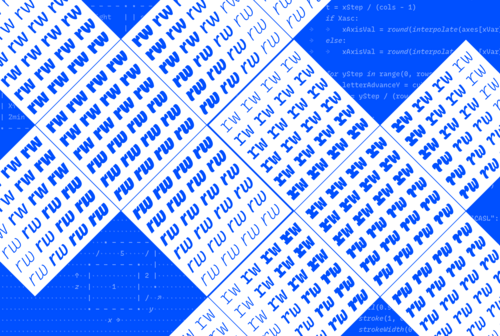
الخط المتغير (VF) هو ملف خط قادر على تخزين نطاق متصل من متغيرات التصميم. يمكن تخزين نمط خط كامل (عائلة خط) في مثل هذا الملف، مع توفر عدد لا نهائي من الخطوط للاختيار من بينها. [ 2 ]
نشأت تقنية الخطوط المتغيرة في تنويعات خطوط TrueType GX من Apple . وتم تكييف هذه التقنية مع OpenType كخطوط OpenType المتغيرة (OTVF) في الإصدار 1.8 من مواصفات OpenType. [ 3 ] [ 4 ] [ 5 ] أعلنت كل من Adobe و Apple و Google و Microsoft عن هذه التقنية في سبتمبر 2016. وقد مهد توحيد هذه الميزة في OpenType الطريق لدعمها في العديد من منصات البرامج. [ 3 ] [ 6 ] [ 7 ] [ 8 ]
لا ينبغي الخلط بين الخطوط المتغيرة والخطوط ذات العرض المتغير . قد يكون الخط المتغير إما ذو عرض متغير أو ذو عرض ثابت . [ 9 ]
تكنولوجيا
تُعدّ خطوط OpenType المتغيرة نسخةً مُعدّلة من خطوط TrueType GX من Apple ، مُدمجةً في OpenType، مع دمجها في جوانب رئيسية من تنسيق OpenType، بما في ذلك جداول تخطيط OpenType وتنسيقات حدود الأحرف الرسومية في كلٍّ من TrueType وCFF. كما أنها تتفوق على TrueType GX بتوفيرها توافقًا أفضل، سواءً بين الخطوط المختلفة، أو بين الخطوط المتغيرة ومواصفات تنسيق الخطوط، مثل تلك الموجودة في أوراق الأنماط المتتالية (CSS). تُمكّن هذه التقنية البرامج من الوصول إلى أي تصميم ضمن نطاق متصل من التصاميم المُعرّفة في الخط. عند اختيار تصميم مُحدد، يتم حساب حدود الأحرف الرسومية أو قيم البيانات الأخرى لهذا التصميم أثناء معالجة بيانات الخط خلال تخطيط النص وتحويله إلى صورة نقطية.
تعتمد هذه التقنية على آليات الاستيفاء والاستقراء المدعومة في أدوات تطوير الخطوط والتي يستخدمها مصممو الخطوط منذ سنوات عديدة. [ 10 ] في هذا النموذج، يُنشئ مصمم الخطوط تصميمًا متغيرًا، ثم يختار نماذج محددة منه لتوليد خطوط ثابتة غير متغيرة تُوزع على العملاء. أما مع الخطوط المتغيرة، فيمكن أن يتمتع الخط الذي يُنتجه ويوزعه مصمم الخطوط بتنوع مُدمج، كما يُمكن الآن دمج آليات الاستيفاء في أنظمة التشغيل ومتصفحات الويب أو التطبيقات الأخرى، مع إمكانية اختيار نماذج تصميم محددة عند الاستخدام.
من أهم مزايا هذه التقنية قدرتها على تقليل حجم بيانات الخطوط بشكل ملحوظ عند استخدام أنماط متعددة. على الويب، يُمكّن هذا الموقع من استخدام المزيد من أنماط الخطوط مع تقليل وقت تحميل الصفحة. كما أنها توفر إمكانية الوصول إلى نطاق واسع من تنويعات الأنماط، مما يُحسّن تصميم المواقع المتجاوبة.
تمت مقارنة هذه التقنية بتقنية الخطوط الرئيسية المتعددة (MM fonts) من أدوبي، والتي ظهرت أيضًا في التسعينيات، حيث كانت تعتمد على توليد تصميمات الخطوط بشكل فوري من الملفات الرئيسية عن طريق الاستيفاء والاستقراء. [ 11 ] [ 12 ] [ 13 ] [ 14 ] مع ذلك، كانت الخطوط الرئيسية المتعددة تتطلب من المستخدم إنشاء "نسخة" محددة من الخط لقيم محور التباين المحددة قبل استخدامه. أما بالنسبة لخطوط OpenType المتغيرة، فلا يتطلب الأمر ذلك: إذ يمكن اختيار نسخ تصميم مُسماة أو عشوائية واستخدامها عند الحاجة.
التبني
أنظمة التشغيل
في نظام التشغيل ويندوز 10، الإصدار 1709 (المعروف أيضًا باسم " تحديث ويندوز 10 للمبدعين الخريفيين") الذي صدر عام 2017، قدمت مايكروسوفت دعمًا رسميًا للخطوط المتغيرة، [ 15 ] إلى جانب أول خط متغير في ويندوز: خط "Bahnschrift"، وهو نسخة رقمية من خط DIN 1451. [ 16 ] [ 17 ] مع ذلك، تسبب دعم خطوط CFF2 باستخدام مخططات OpenType في مشاكل مع محرك عرض النصوص في ويندوز، مما أدى أحيانًا إلى اختفاء نص واجهة المستخدم؛ وقد تم إصلاح هذه المشكلة لاحقًا في عام 2023 مع تحديث KB5032278. [ 18 ]
بدأ نظام Android في توفير دعم الخطوط المتغيرة لمطوري تطبيقات الهاتف المحمول في Android Oreo [ 19 ] أو مستوى API 26. [ 20 ]
وفرت شركة Apple دعم الخطوط المتغيرة في نظام التشغيل الخاص بها منذ macOS 10.5/ iOS 3.2 ، [ 21 ] ولكن استخدامها في Safari من خلال WebKit لا يتوفر إلا في macOS 10.13/iOS 11 مع Safari 11. [ 22 ] [ 23 ]
حصل برنامج FreeType ، وهو برنامج عرض الخطوط المستخدم في معظم الأنظمة الشبيهة بنظام Unix ، بما في ذلك Linux ، على دعم الخطوط المتغيرة في مايو 2017 (FreeType 2.8). [ 24 ]
المحررون
يتضمن إصدار Adobe Creative Cloud 2018، الذي صدر في 18 أكتوبر 2017، دعمًا للخطوط المتغيرة في Photoshop [ 25 ] و Illustrator [ 26 ] ويتضمن إصدارات مفاهيم متغيرة من الخطوط Acumin و Minion و Myriad و Source Code و Source Sans و Source Serif .
أضافت Creative Cloud 2020 دعم الخطوط المتغيرة لبرنامج InDesign . [ 27 ]
أضاف الإصدار 1.0 من برنامج Inkscape دعمًا للخطوط المتغيرة. [ 28 ]
أضاف الإصدار 7.5 من LibreOffice دعمًا للخطوط المتغيرة. [ 29 ]
المتصفحات
يتم التحكم في الخطوط المتغيرة في متصفح الويب باستخدام كلٍ من الخصائص الموجودة للخيارات المعروفة مثل الوزن وعنصر font-variation-settingsتحكم أساسي. راجع صفحات MDN الخاصة بخاصية CSS للاطلاع على تاريخ الدعم. [ 2 ]